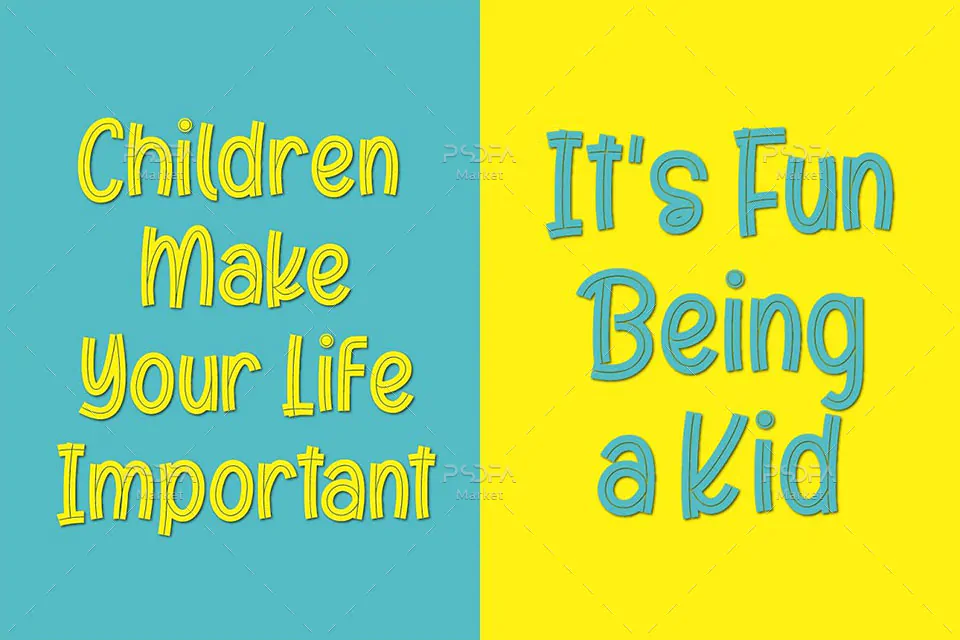
فونت کودکانه و کارتونی فوق العاده زیبا Kids Place یک قلم انگلیسی است که مناسب جهت استفاده در طرحهای گرافیکی مختلف به خصوص طراحی انواع تصاویر کودکانه و کارتونی میباشد. این فونت زیبا در قالب 3 فایل OTF, TTF, WOFF در فایل محصول قرار دارد که با نصب یکی از 2 فرمت ttf یا otf در پوشه فونتهای سیستم میتوانید از این فونت انگلیسی در تمام نرم افزارهای گرافیکی و تایپ متون همچون فتوشاپ، افتر افکت، پریمیر، ورد، پاورپوینت و … استفاده کنید.
فونت Kids Place در سه وزن معمولی (Regular) باریک (Inline) و ضخیم (Clean) طراحی شده است که میتوانید از آن در طراحی بسته بندی محصولات، لوازم التحریر، بگهای خرید و هدیه، ظروف یکبار مصرف، رابط گرافیکی گیم، تقویم، پوستر، بنر، بروشور، تراکت، طراحی صفحات وب، چاپ تیشرت و دیگر طرحهای گرافیکی استفاده کنید.
- کیفیت بالای قلم
- نام فونت: Kids Place
- وزن: Regular, Inline, Clean